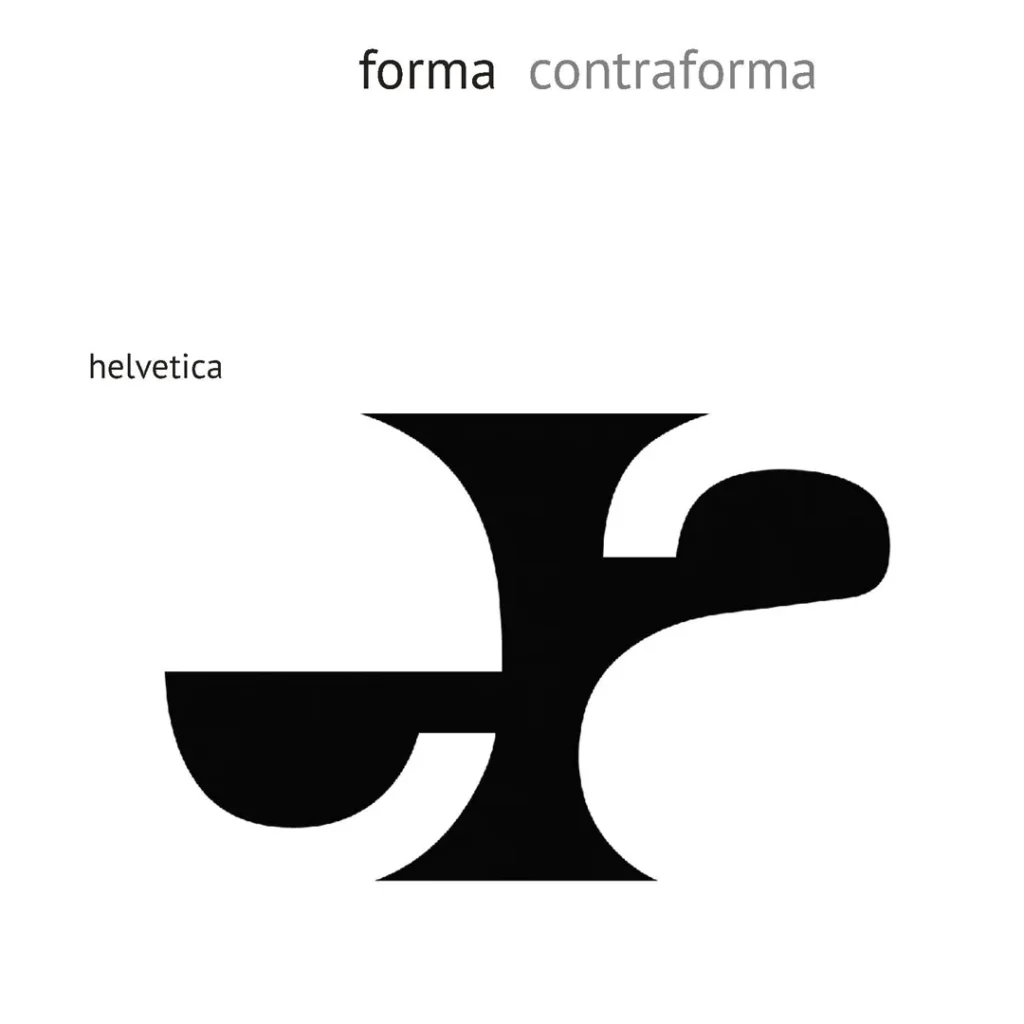
FORMA Y CONTRAFORMA
Es el espacio negativo de los signos. Existen contraformas internas y externas. A las contraformas internas se las puede denominar como “ojo” de una letra. Las contraformas externas son particularmente importantes a la hora de definir cuál es el espacio que debe ocupar un signo cuando se encuentra en relación a otros (kerning e interletrado).
Como regla general, cuando la contraforma externa es menor, se necesita mayor espacio de separación entre los signos. Cuando la contraforma externa es amplia, se permite mayor cercanía. La terminación en serif ayuda a establecer las distancias mínimas en que los signos pueden ubicarse.